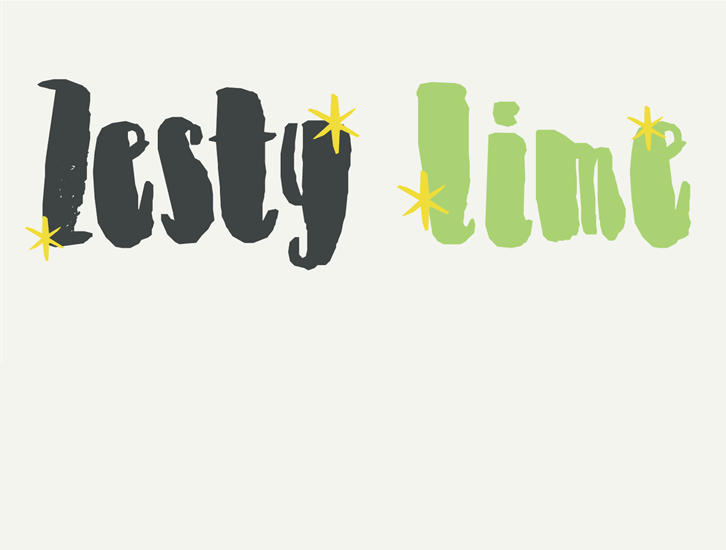
DK Zesty Lime Font
Aqui está uma descrição envolvente para a página de download da fonte ‘DK Zesty Lime Font’, focada em seu estilo fresco e limpo: Assegure-se de manter seu design moderno com DK Zesty Lime, uma elegante fonte brush que não deixa dúvidas sobre o estilo jovial e alegre que você deseja imbuir ao seu projeto. Inspirado na riqueza vibrante do laranja fresco e cheio de energia, essa fonte é perfeita para destacar seus textos em espaços onde um toque de vitalidade será bem-vindo. Ideal tanto para o texto principal quanto para títulos chamativos ou tags interessantes, DK Zesty Lime traz consigo uma dose de brilho e vida que vai fazer seu trabalho falar por si só. Quer que essa fonte seja a estrela da sua próxima criação? Não hesite em comprar a versão completa do full package. Nesta versão demo, você terá acesso aos elementos essenciais e ao estilo vibrante de DK Zesty Lime, mas se desejar incorporar seu design em jogos, aplicativos ou software, então é hora de considerar a licença adicional que oferecemos no site oficial da Hamilton. Assim, você pode garantir o uso seguro e legítimo dessa fonte, preservando não apenas sua própria reputação como criador, mas também seu produto final.